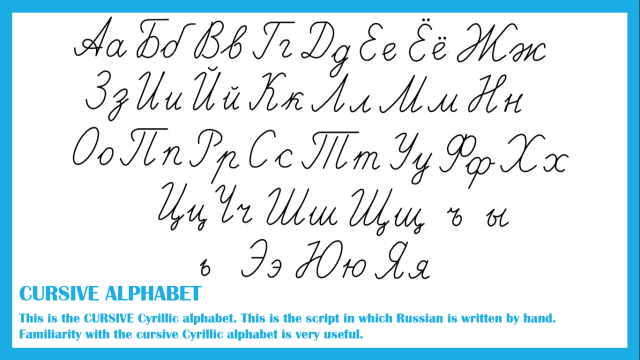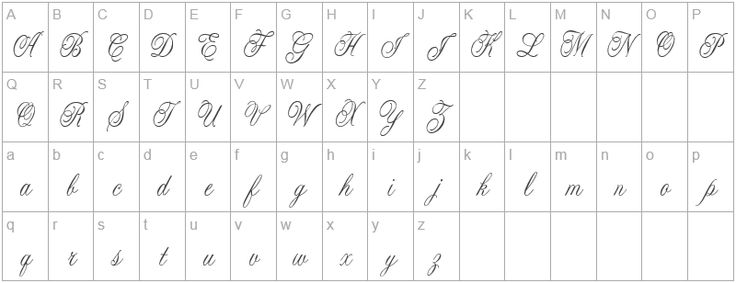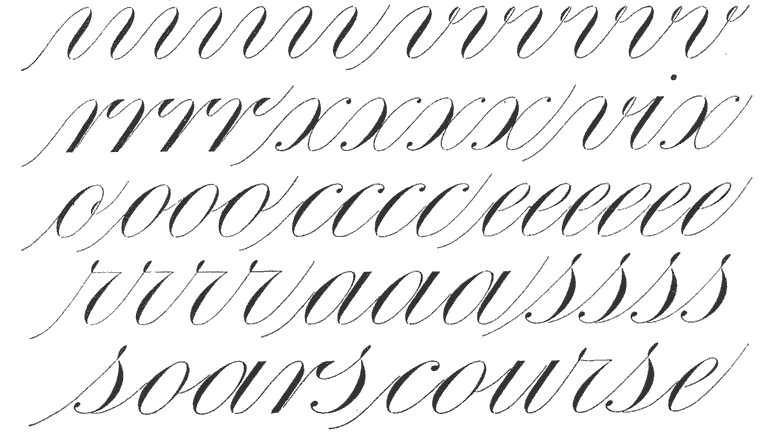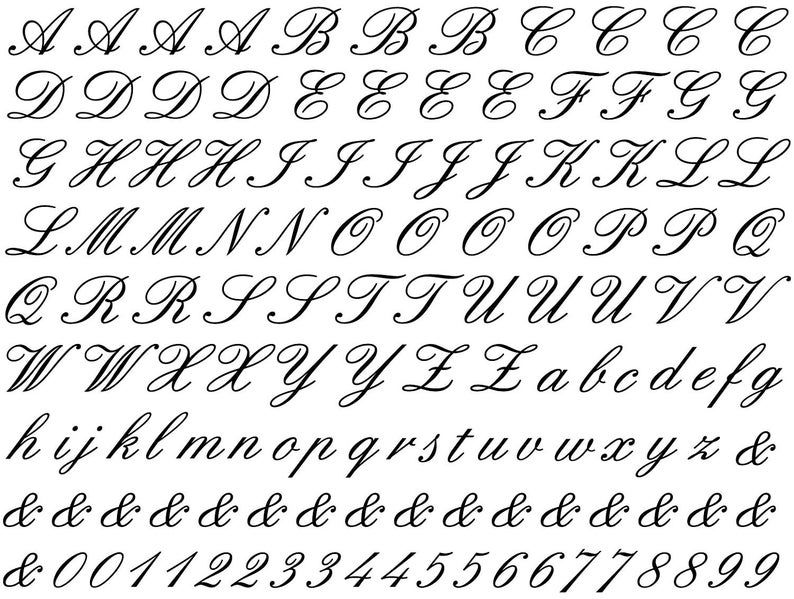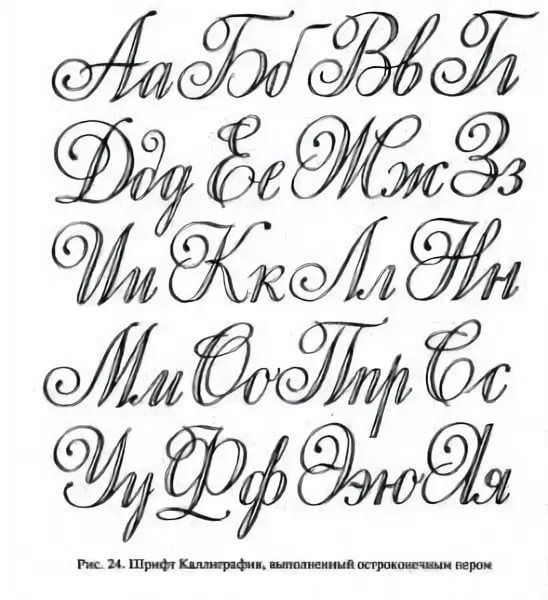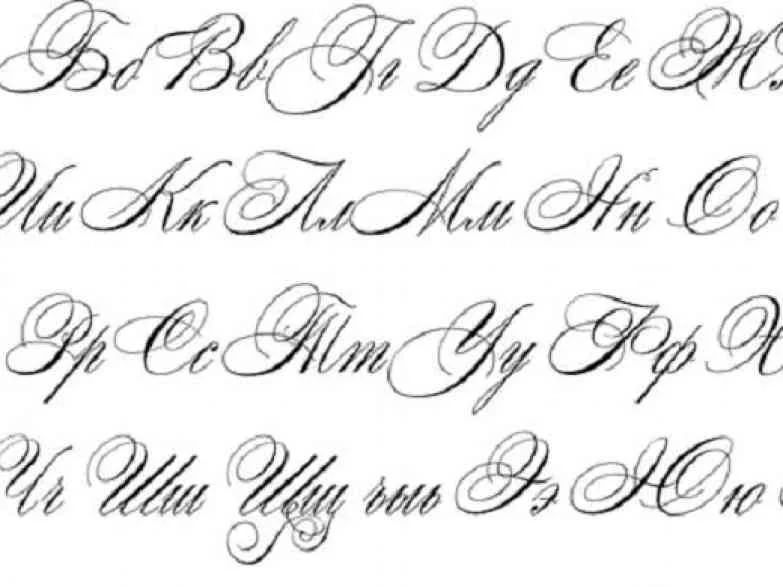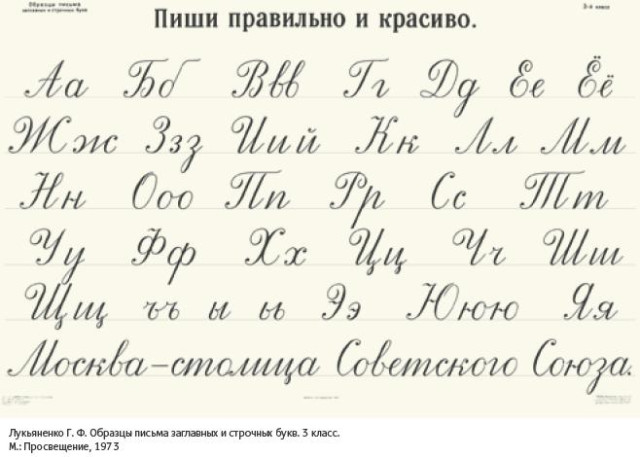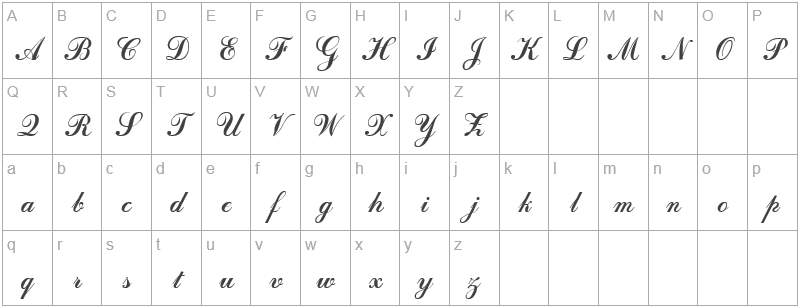
Шрифт прописью красивый: Лучшие 20 рукописных и каллиграфических шрифтов для презентации
Шрифт на латыни для тату (47 фото)
Красивые шрифты для татуировок на латинском
Образцы шрифтов
Шрифты для тату для девушек
Шрифты для татуировок
Английские буквы красивым шрифтом
Каллиграфическая надпись на латыни
Тату шифр
Современные Каллиграфические шрифты
Каллиграфические буквы английские
Каллиграфия названия шрифтов
Красивые прописные буквы
Рукописные шрифты для тату
Спенсериан и копперплейт
Тату буква а
Готический шрифт латынь